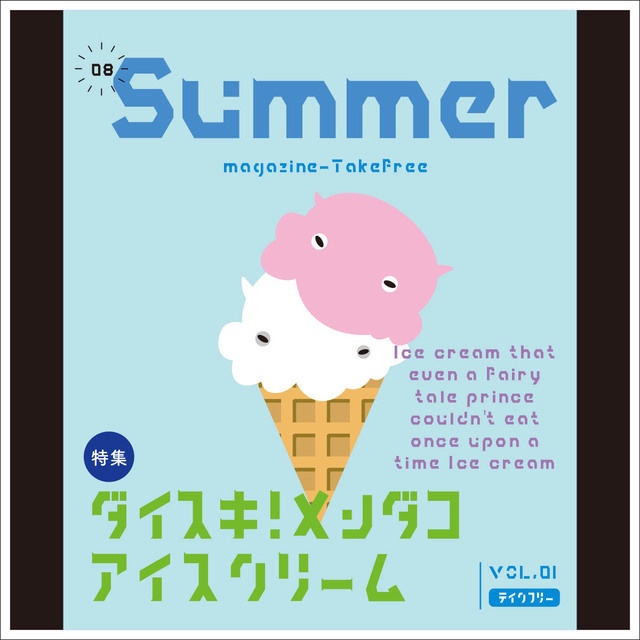
213chan-font【商用可】
この213chanフォントは213ちゃんがはじめての作った 商用可のフリーフォント(freefont)です。 印刷物・ゲームやWeb、YouTubeのサムネイルやタイトルデザインなどにいかがでしょうか? 基本フリーですが、当フォントを利用した制作物などを、SNSで教えてくれると励みになります。 制作時のお気に入りポイントをnoteで記事にしています。 ぜひ遊びにきてね!スキお待ちしています。 https://note.com/sweet_2727/n/n60fbbdd04980 【収録内容】アルフファベット(大文字・小文字)カタカナ・少しの記号 【Readme】フォントご使用上の注意 ・フォントの著作権は、213ちゃんに帰属します。 ・可愛がってくださるとうれしいです。 ・無断転載・再配布は堅くお断りいたします。 ・DLしたフォントに起因する損害は補償致しかねますので予めご了承ください。 ・使用する際の不明点はお問い合わせ先にご連絡ください。答えられる範囲でお返事いたします。